「もちもち」の雰囲気にぴったりな日本語フリーフォント15選
丸くて、やわらかくて、思わず触れたくなるような「モチモチ」の雰囲気。おもち、マシュマロ、グミ、肉球、ふわふわしたキャラクターなど、やさしく可愛い世界観を作りたいときは、文字の形もとても大切です。
今回は、もちっとした丸みや、ぽてっとした太さ、手書きらしい温かさを持つ日本語フリーフォントをピックアップしました。ロゴ制作、YouTubeサムネイル、SNS画像、お菓子パッケージ、キッズ向けデザインなど、やわらかい印象を出したい場面で使いやすいフォントばかりです。
モチモチ感たっぷりのかわいい日本語フリーフォント
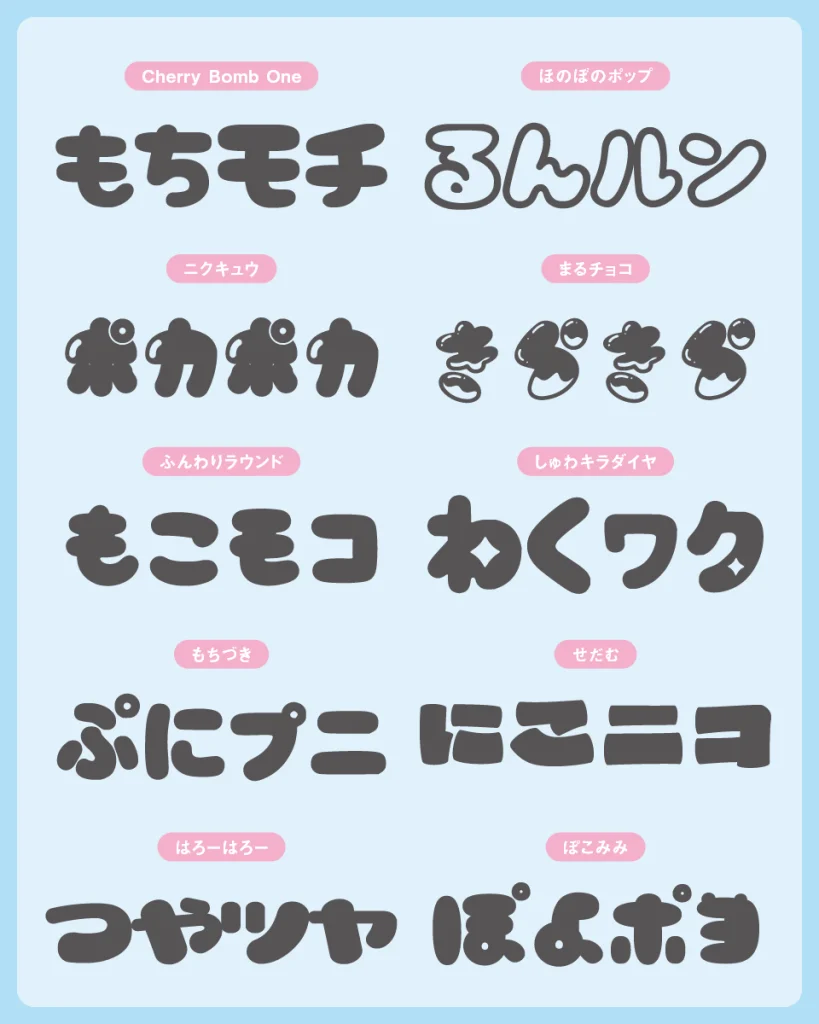
づにのい(Mike)
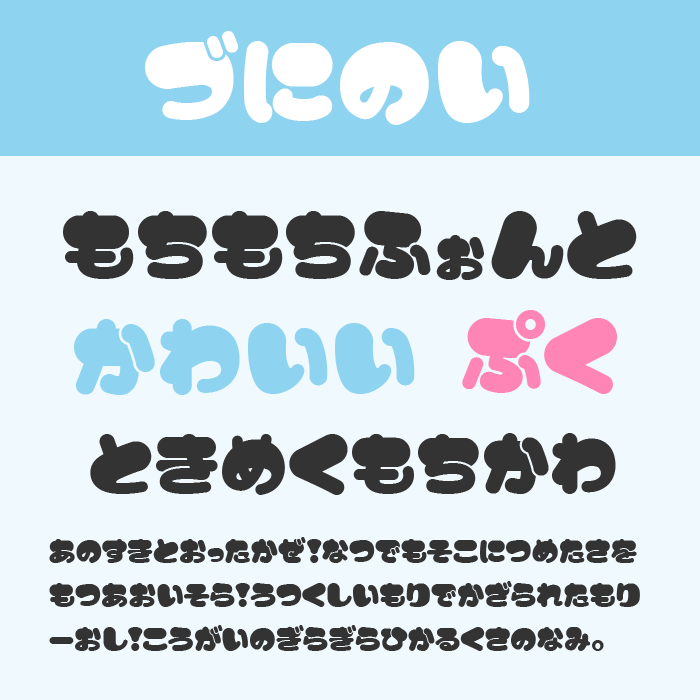
| 使用用途 | 見出し/タイトルロゴ/短いコピー |
| おすすめの世界観 | おもち・ぷにぷに/ゆるキャラクター/お菓子パッケージ/子ども向け |
づにのい(Mike)は、ぷくっと膨らんだひらがなが印象的なデザインフォントです。文字ごとに太さや形の揺らぎがあり、きれいに整いすぎていないところに手作りのおもちのような可愛さがあります。
長文よりも短い言葉やタイトル向きで、「もちもち」「ぷにぷに」といった質感をそのまま文字で見せたいときにぴったり。スイーツ系のアイキャッチや、ゆるいキャラクター名にもよく合います。
まるチョコ
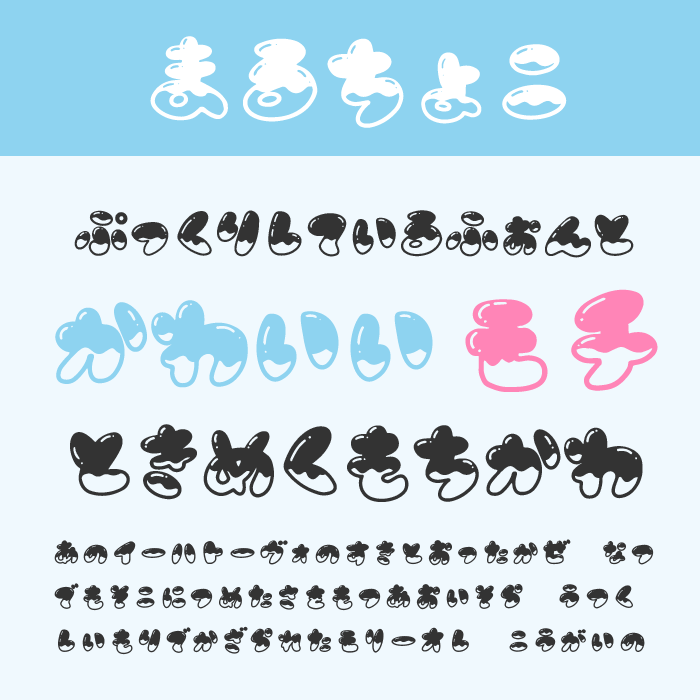
| 使用用途 | 見出し/タイトルロゴ/お菓子系デザイン |
| おすすめの世界観 | チョコレート/ドーナツ/バレンタイン/甘いおやつ/ファンシー |
まるチョコは、丸い手書き文字にチョコレートがとろりとかかったような、甘くて楽しいデザインフォントです。
お菓子やパンを思わせる見た目なので、「モチモチ」というテーマにも自然になじみます。文字そのものにデコレーション感があるため、ベタ打ちでも可愛いロゴのように見せやすいのが魅力。バレンタイン、スイーツショップ、手作りおやつの告知など、甘さを前面に出したい場面で使いやすいフォントです。
ぽこミミ
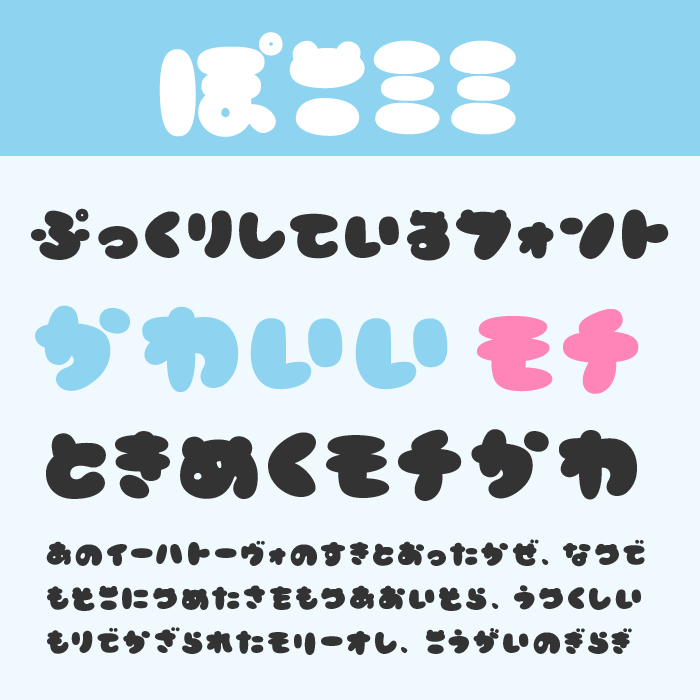
| 使用用途 | 見出し/タイトルロゴ/キャラクター系デザイン |
| おすすめの世界観 | たぬきモチーフ/ほっこり/キッズ/雑貨/ポップなイベント |
ぽこミミは、文字に小さな耳のような装飾がついた、遊び心たっぷりのデザインフォントです。
ぷっくりした輪郭と丸いシルエットが可愛らしく、見ているだけでほっこりした気分になります。モチモチ感を表現する場合は、やわらかい食べ物そのものよりも、キャラクターや雑貨のような親しみやすさを出したいときに向いています。子ども向けの見出し、イベント名、かわいいSNS画像などに使うと印象的です。
もちづき(望月)
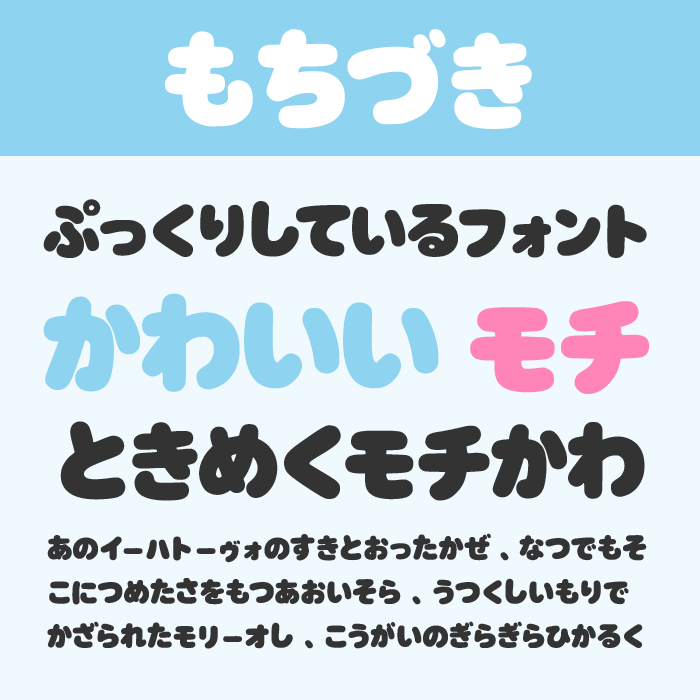
| 使用用途 | 見出し/タイトルロゴ/サムネイル/パッケージ |
| おすすめの世界観 | おもち/マシュマロ/ゆるふわ/Vtuberサムネ/かわいいバナー |
もちづきは、名前の通りおもちのような弾力を感じる、丸く太めのデザインフォントです。
線の太さにほんの少し揺らぎがあり、ふっくらとした形の中に手書きらしい温かさが残っています。太さはあるのに圧が強すぎず、やさしく親しみやすい雰囲気を作れるのが魅力です。「モチモチ」のテーマでは中心に置きやすい一書体で、お菓子パッケージ、ポップなバナー、かわいいタイトル制作に特に合います。
せだむ
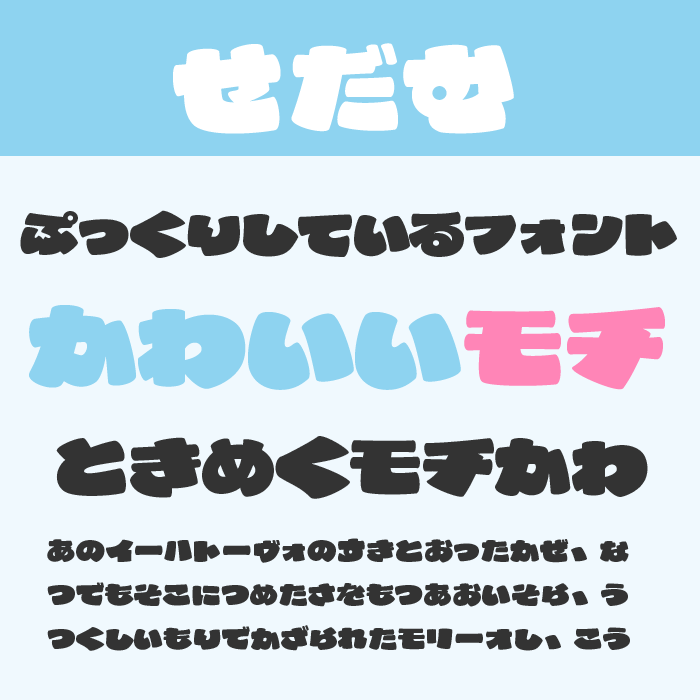
| 使用用途 | 見出し/タイトルロゴ/インパクト系デザイン |
| おすすめの世界観 | マシュマロ/極太ポップ/推し活/Vtuber/目立つサムネイル |
せだむは、極太のストロークと大胆な丸みが目を引く、存在感のあるポップなデザインフォントです。
文字の輪郭がぷっくり膨らんでいて、マシュマロを重ねたような柔らかさと重みがあります。やさしいだけでなく、しっかり目立つ「モチモチ感」を出したいときに向いており、サムネイルやロゴで使うと一気に主役感が出ます。短い言葉を大きく見せるほど、ぽってりした可愛さが伝わりやすいフォントです。
プぷプ
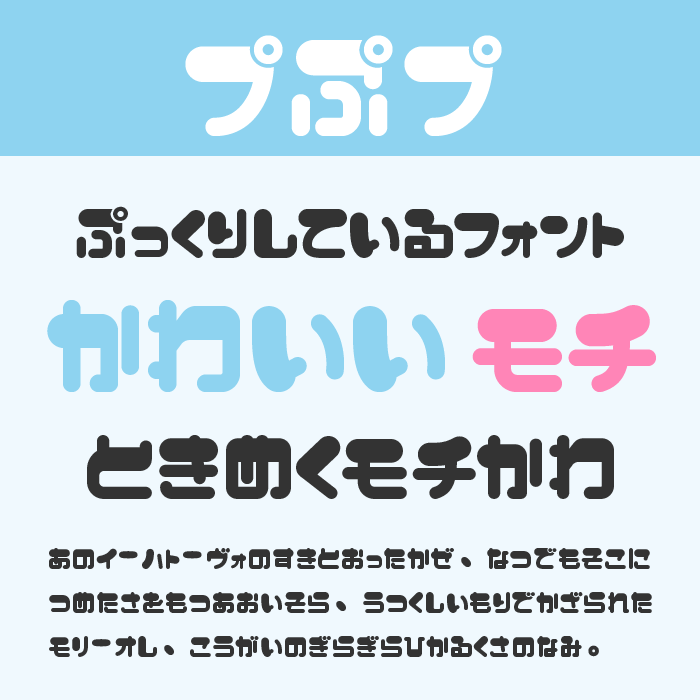
| 使用用途 | 見出し/本文/タイトルロゴ |
| おすすめの世界観 | レトロポップ/ゲーム風/コミカル/オノマトペ/個性派ポップ |
プぷプは、文字の上部が太く、下に向かって少し細くなる個性的なシルエットが楽しいフォントです。
角丸の太い形が印象に残りやすく、レトロゲームのような雰囲気と、丸文字らしい可愛さを両方持っています。おもちのような素直な柔らかさというより、「ぷにっ」「ぽよん」とした擬音の表現に向いているタイプ。見出しや短いコピーに使うと、コミカルで明るいモチモチ感を作れます。
鳩とブリキのワンダランド
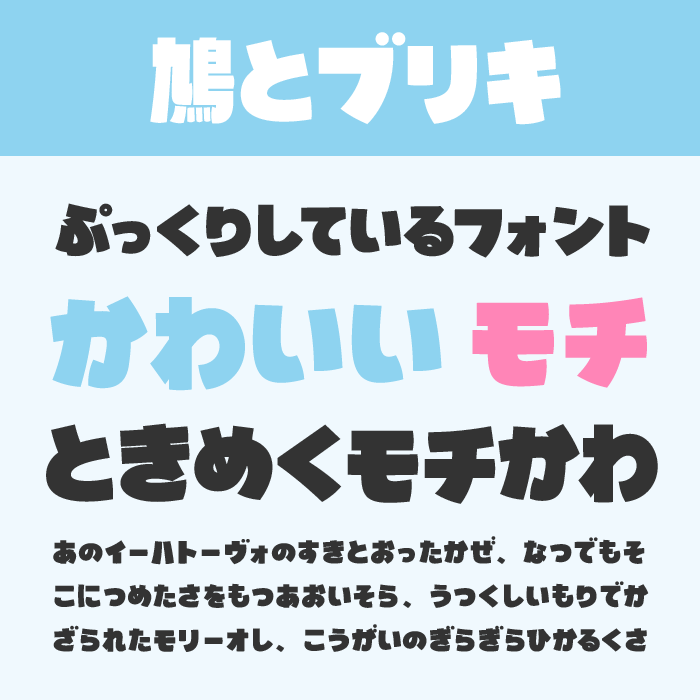
| 使用用途 | 見出し/タイトルロゴ/レトロポップ |
| おすすめの世界観 | 昭和レトロ/おもちゃ箱/手作り感/ポスター/個性派パッケージ |
鳩とブリキのワンダランドは、極太でどっしりしたシルエットに、少しレトロな可愛さを感じるデザインフォントです。
文字の傾きやバランスに手作り感があり、きっちり整ったフォントにはない温もりがあります。モチモチ系の中でも、素朴で懐かしいお菓子や、昔の玩具パッケージのような世界観に合わせやすい書体です。短いタイトルに使うと、重量感と親しみやすさが同時に出せます。
はろーはろー
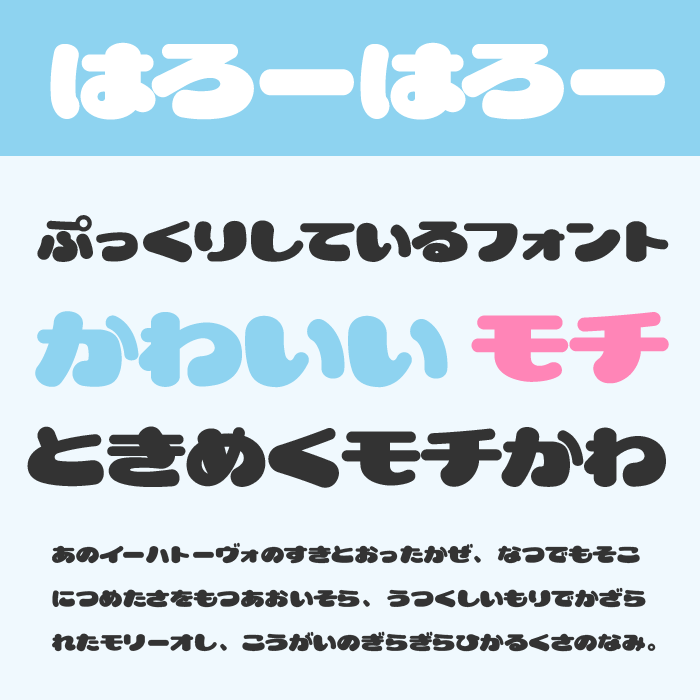
| 使用用途 | 見出し/タイトルロゴ/POPデザイン |
| おすすめの世界観 | 80〜90年代レトロ/ゆるかわ/お菓子/イベント告知/かわいいタイトル |
はろーはろーは、ふっくらとした丸みとやさしい柔らかさが魅力のデザインフォントです
線の太さが均一ではなく、文字全体がぽてっとしているため、弾力のあるモチモチした雰囲気を出しやすい一書体です。どこか80〜90年代のレトロポップ感もあり、明るく懐かしい可愛さを作れるのが特徴。お菓子、イベント告知、子ども向けのタイトルなど、親しみやすさを大切にしたいデザインに向いています。
しゅわキラダイヤ
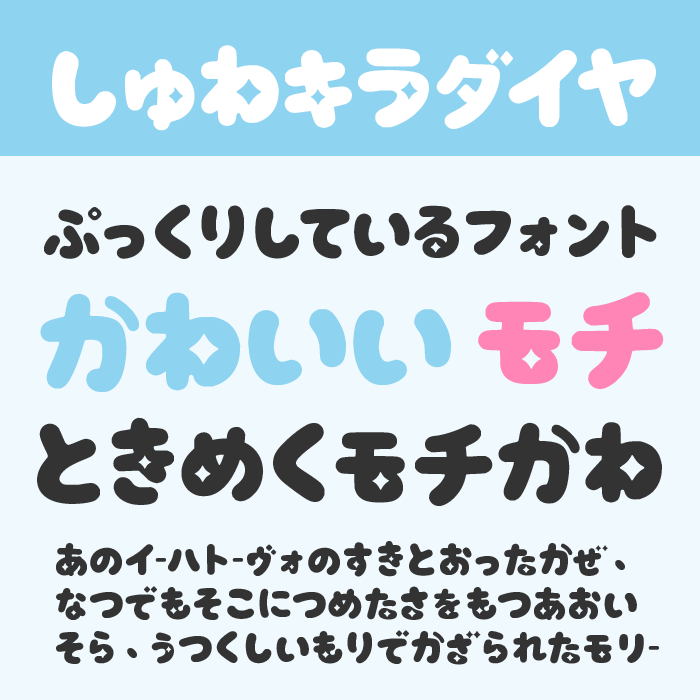
| 使用用途 | 見出し/タイトルロゴ/アイドル風デザイン |
| おすすめの世界観 | キラキラ/炭酸/推し活/Vtuber/ゆめかわ/キッズ |
しゅわキラダイヤは、丸みのある太字に小さなダイヤのような装飾が入った、華やかで可愛らしいフォントです。
ぷっくりしたシルエットに、炭酸の泡が弾けるような軽さが加わっていて、甘いだけで終わらない楽しさがあります。「モチモチ」の中でも、マシュマロソーダやキラキラしたスイーツのような世界観にぴったり。アイドル風ロゴ、Vtuberサムネイル、キッズ向けデザインで明るく目立たせたいときに使いやすいフォントです。
ふんわりラウンド
| 項目 | 内容 |
| 商用利用 | 商用利用可 |
| 収録文字 | ひらがな/カタカナ/英字/数字/一部記号 |
| 使用用途 | 見出し/タイトルロゴ/やさしいデザイン |
| おすすめの世界観 | ふわふわ/雲/子ども向け/ナチュラル/ゆるふわバナー |
ふんわりラウンドは、やや手描き風の骨格に、丸ゴシックのような太めの先端丸を合わせた柔らかなフォントです。
雲のようにふわっとした丸みがあり、強い主張よりも、安心感ややさしさを伝えるのが得意です。モチモチ系の中では、軽くて空気を含んだような質感を出したいときに向いています。子ども向けの見出し、ナチュラルなバナー、手作り感のあるお知らせなどに使うと、やわらかい印象にまとまります。
みきゆフォント もこもり黒β
| 項目 | 内容 |
| 商用利用 | 商用利用可 |
| 収録文字 | 漢字一部/ひらがな/カタカナ/英字/数字/一部記号 |
| 使用用途 | 見出し/タイトルロゴ/手書きPOP |
| おすすめの世界観 | もこもこ/ガーリー/雑貨/手作りPOP/かわいいSNS投稿 |
みきゆフォント もこもり黒βは、モコモコとした輪郭がガーリーで可愛らしい手書き風フォントです。
きれいに整えすぎない手書き感があり、文字に触れたくなるようなふくらみがあります。モチモチ感を表現するときは、素朴で親しみやすい雰囲気づくりに向いています。雑貨デザイン、手書きPOP、かわいいSNS投稿など、作り込みすぎない自然体の可愛さを出したい場面で使いやすいフォントです。
モフ字
| 項目 | 内容 |
| 商用利用 | 商用利用可 |
| 収録文字 | 漢字/ひらがな/カタカナ/英字/数字/記号 |
| 使用用途 | 見出し/本文/タイトルロゴ |
| おすすめの世界観 | モフモフ/手書きPOP/ナチュラル/ハンドメイド/ゆるかわ |
モフ字は、角のない曲線で作られた、モフモフとした質感が楽しいデザインフォントです。
規則的すぎない形と、少しにじんだような線の雰囲気があり、手書きの温かさと不思議な可愛さが混ざっています。モチモチというテーマでは、やわらかい毛並みや丸いぬいぐるみのような方向で使うと相性が良いフォントです。ナチュラル系のバナー、ハンドメイド作品、ゆるい見出しなどに使うと味が出ます。
Cherry Bomb One(チェリーボム)
| 使用用途 | 見出し/タイトルロゴ/バナー/同人誌タイトル |
| おすすめの世界観 | 海外ポップ/レトロ/ガーリー/アパレルロゴ/ポスター |
Cherry Bomb One(チェリーボム)は、ぷくぷくとした丸いフォルムが可愛らしいかな文字フォントです。
太めのペンで書いたような手書き感があり、柔らかさとインパクトのバランスがとても良い書体です。モチモチ系の中でも、少し海外ポップやレトロガーリーに寄せたいときに向いています。サムネイル、バナー、同人誌タイトル、アパレル風のロゴなど、かわいく目立たせたい場面で使いやすいフォントです。